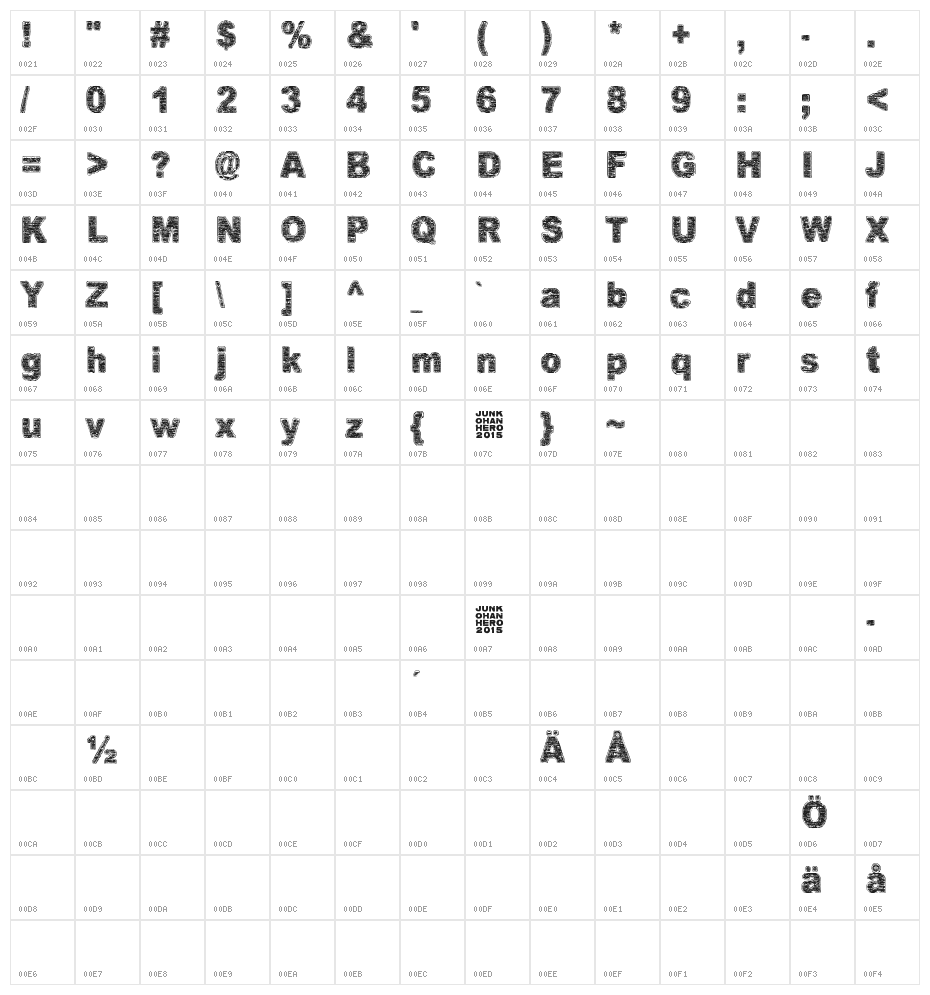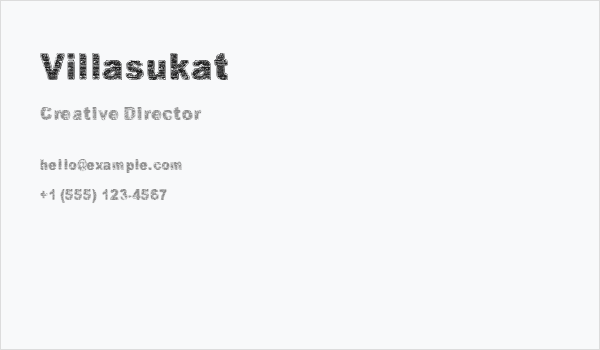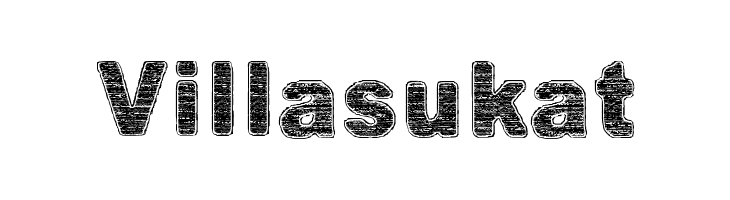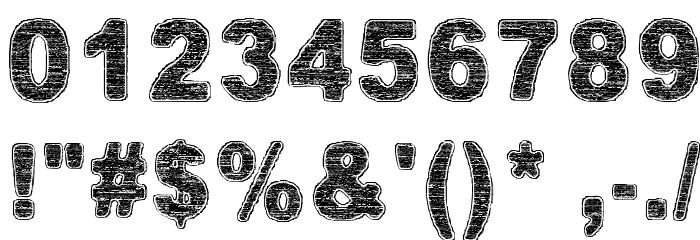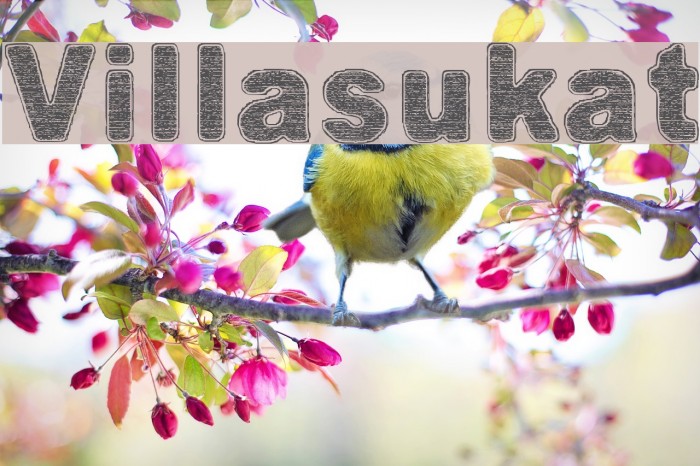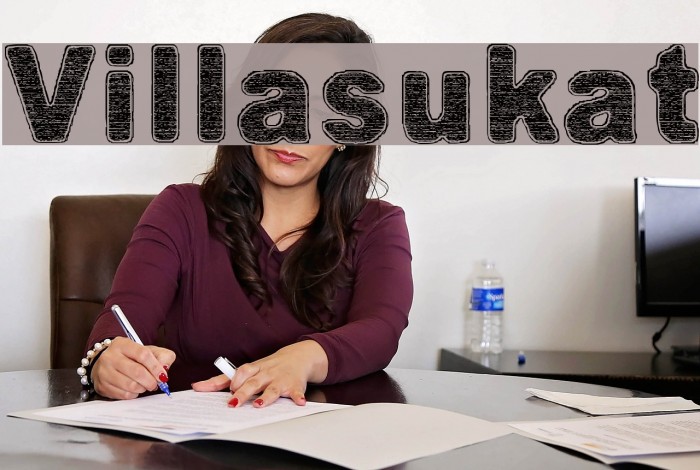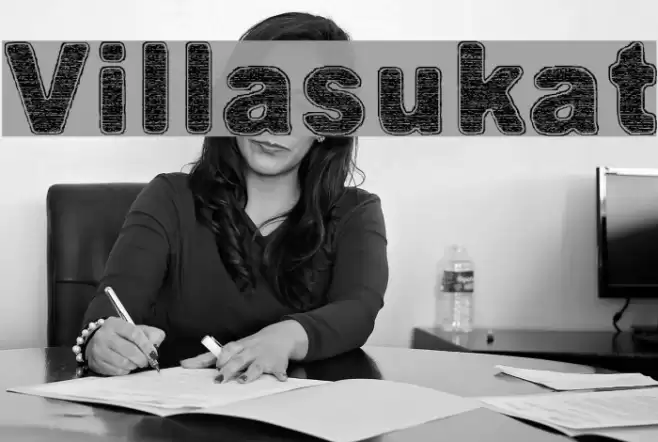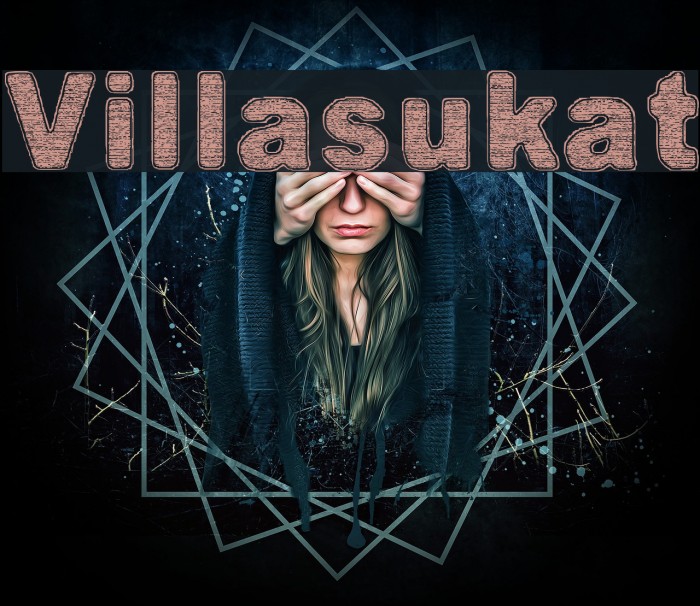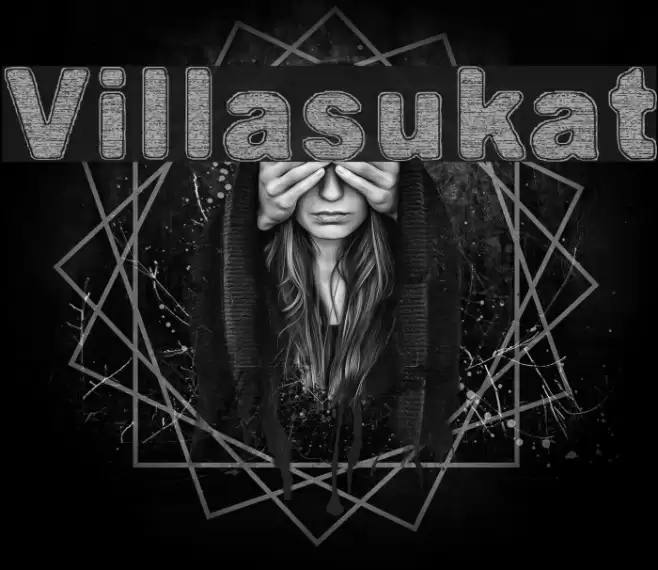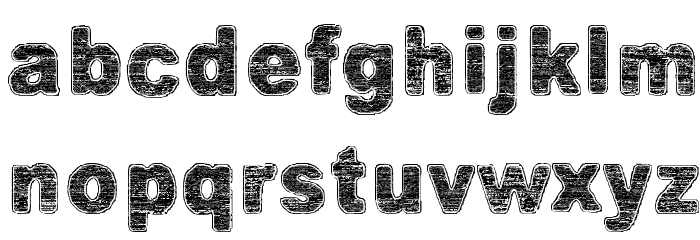
Villasukat Font
✎ Distorted Eroded
| Categorii | Distorted Eroded |
| Proiecte propuse | Ideal for posters, album covers, branding, and any design needing a bold, vintage touch. |